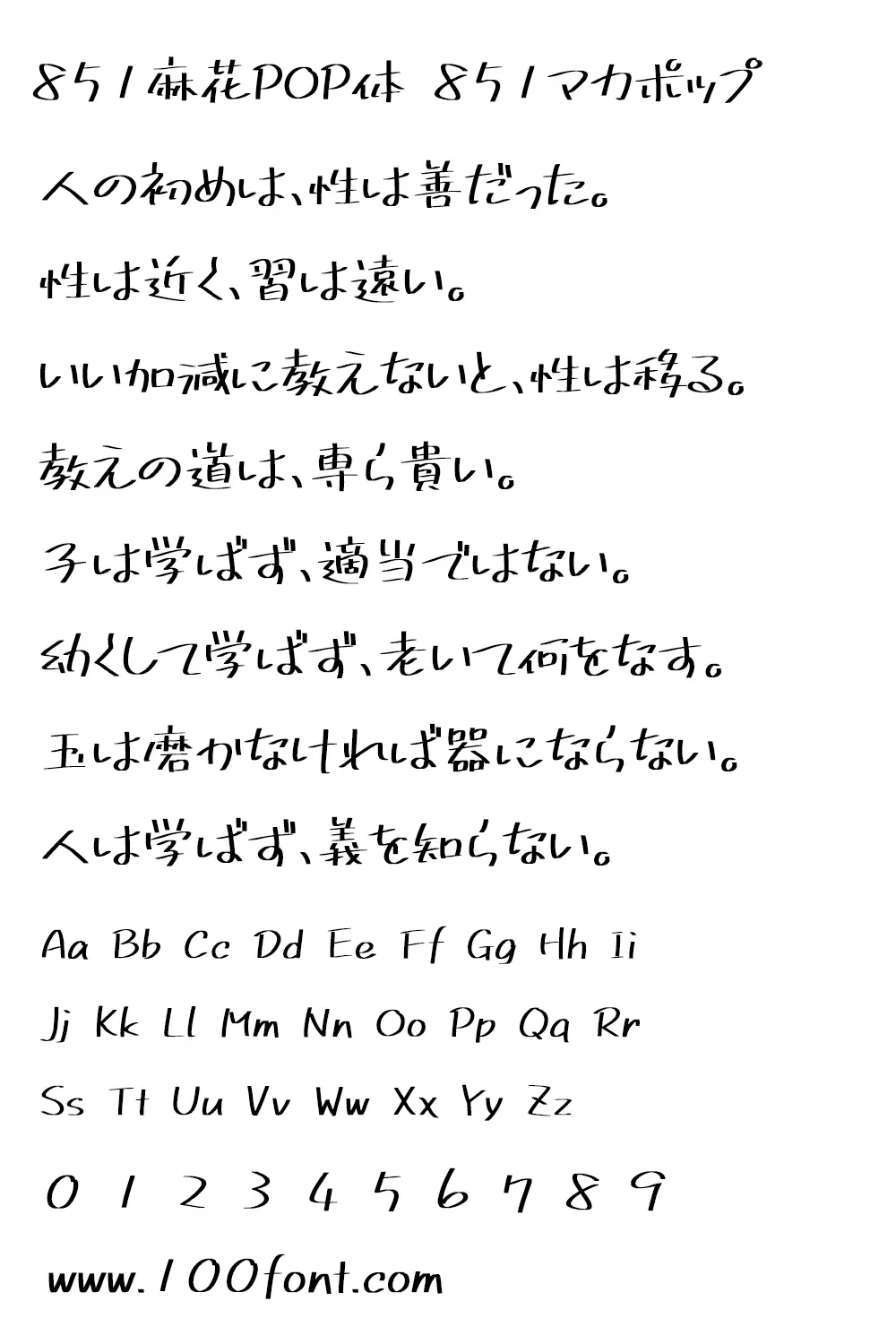
851麻花POP體(851マカポップ)是由日本設計師 8:51:22 pm設計的一款橫粗的日文手寫字體,當前字符數:9620個字符(不包括空格)。
對應文字:JIS X0208(Shift-JIS)的全部文字(全部JIS第1、第2水準漢字),Unicode“拉丁輔助”,JIS外漢字中可能有用途的數千個文字。
注意:這款字體適用於繁體和日文,不適用於簡體中文,容易缺字。